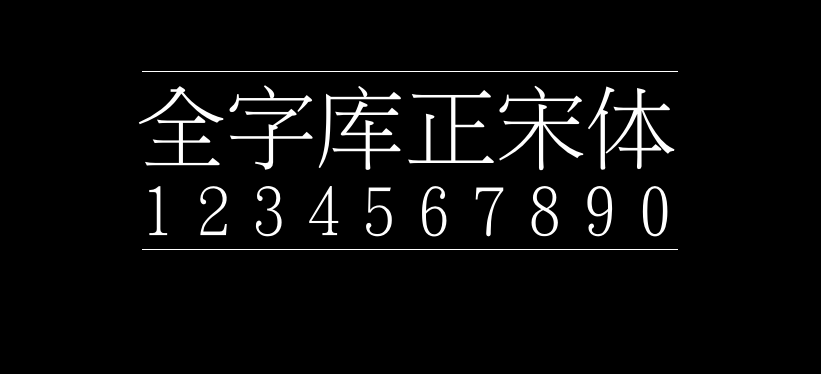
全字库正宋体
全字库正宋体(TW-Sung)来自中国台湾为了统一资料交换使用的内码而制定的标准字元编码方案,标准交换码让不同内码也可以沟通交换内容;全字库正宋体就来源于该计划推出的全字库。
这两款字体是为了早期中国台湾统一资料内码而制定的编码方案,设计上没有什么特色,中规中矩。字符集相对来说也比较全,简体繁体基本都不缺字,喜欢的朋友可以下载试试!